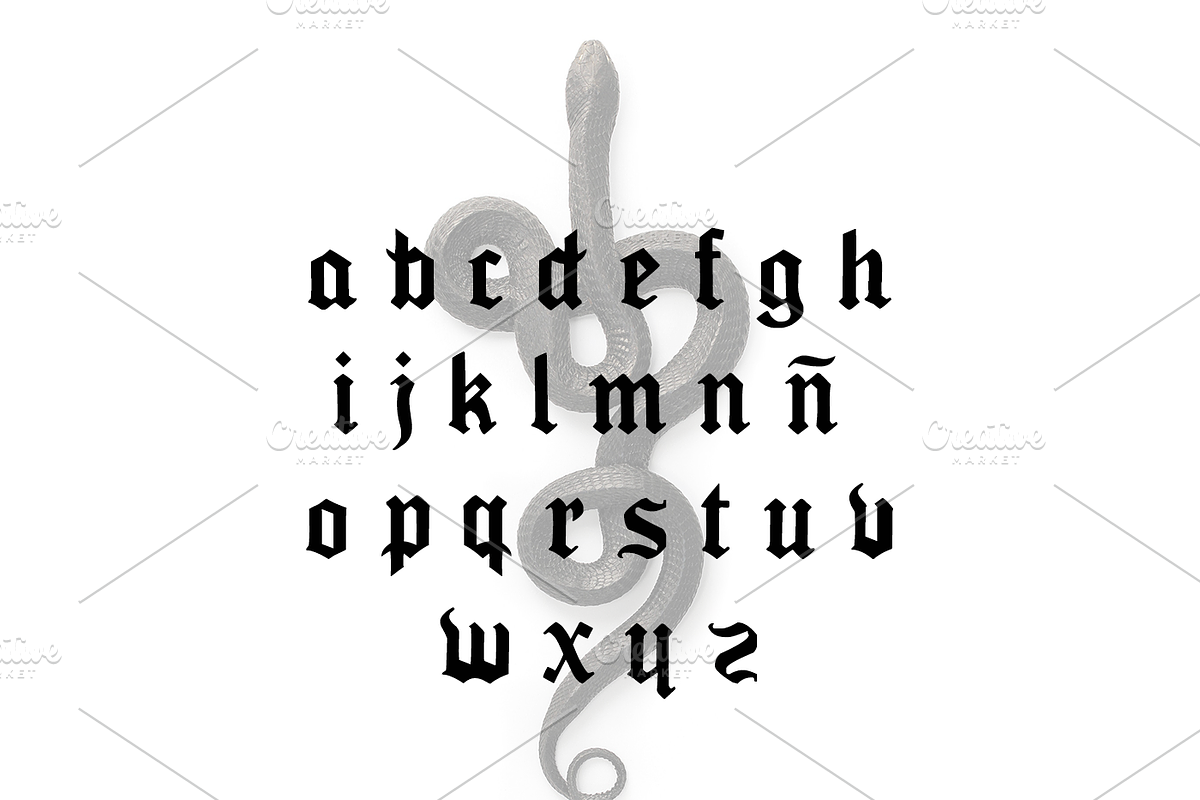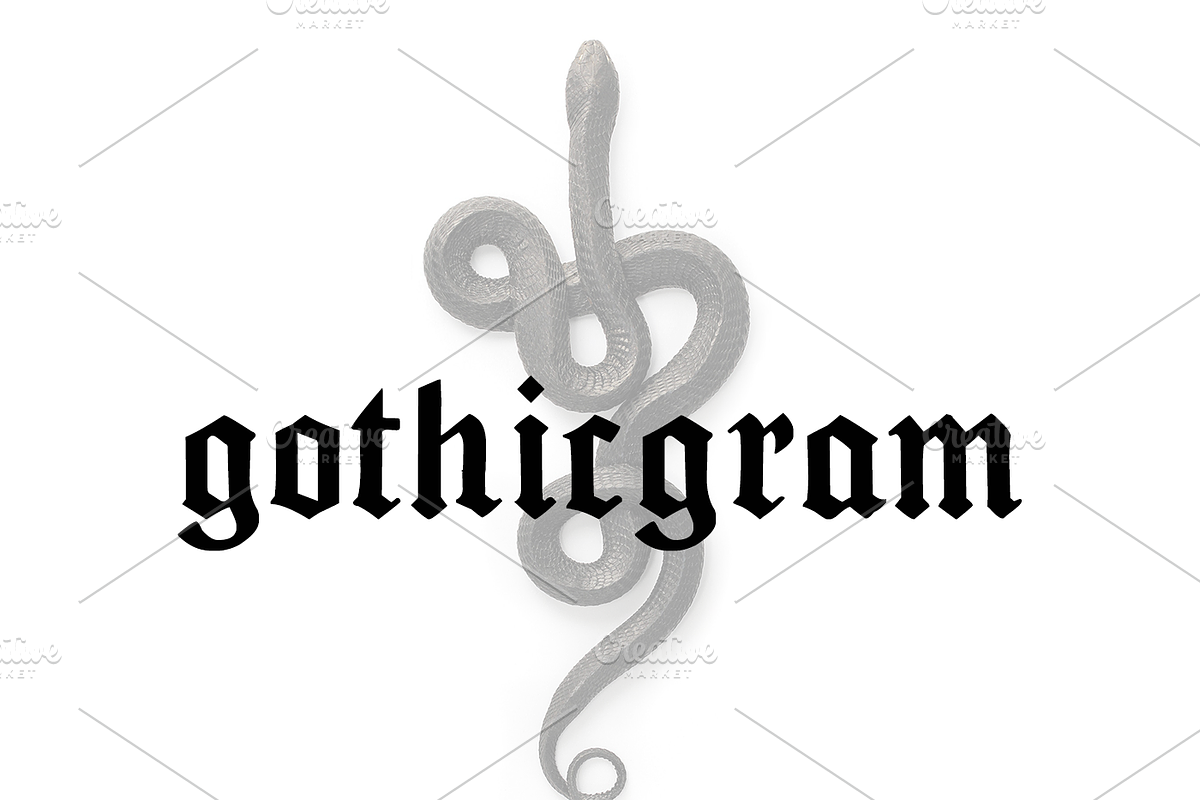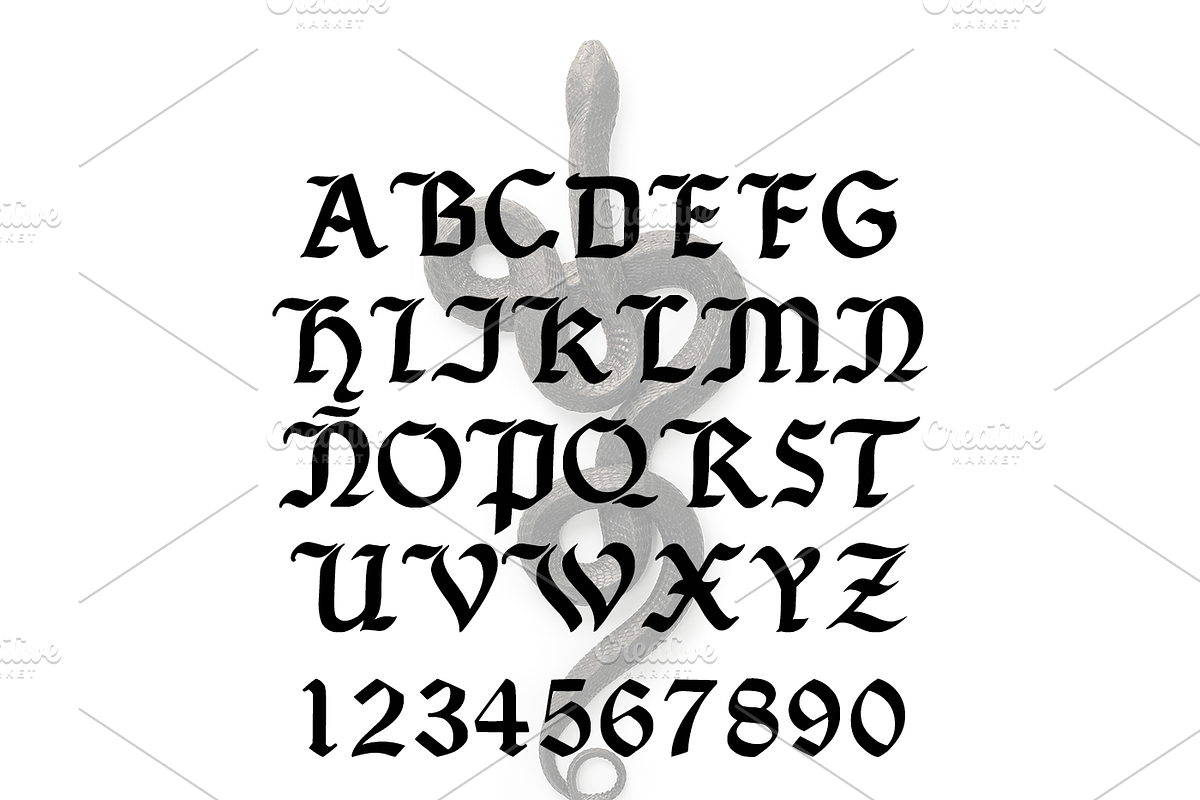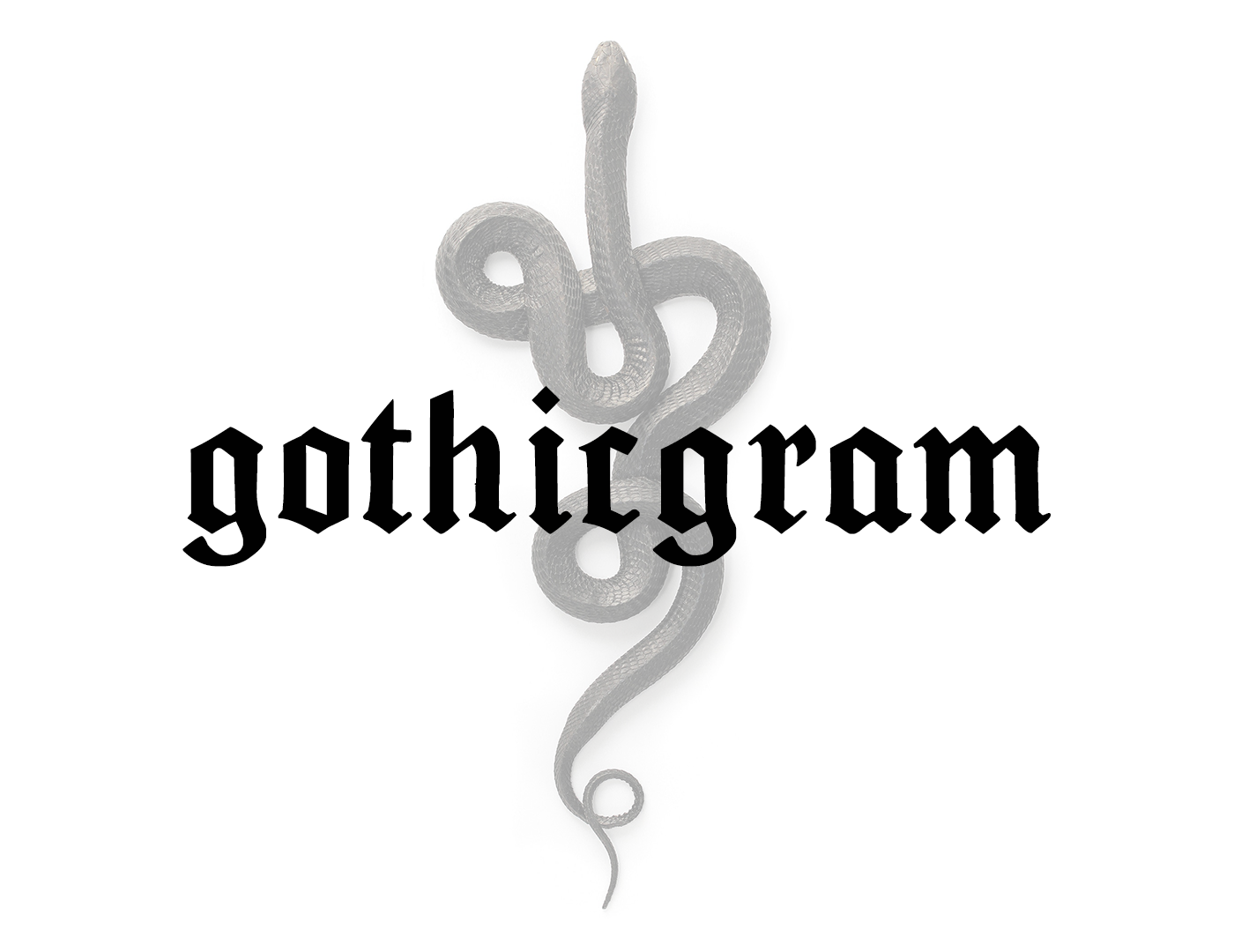
gothicgram font
Descubre GothicGram, una tipografía elegante y moderna con un toque gótico. Perfecta para proyectos creativos, diseños de marca y títulos impactantes. ¡Haz que tus diseños destaquen con GothicGram!